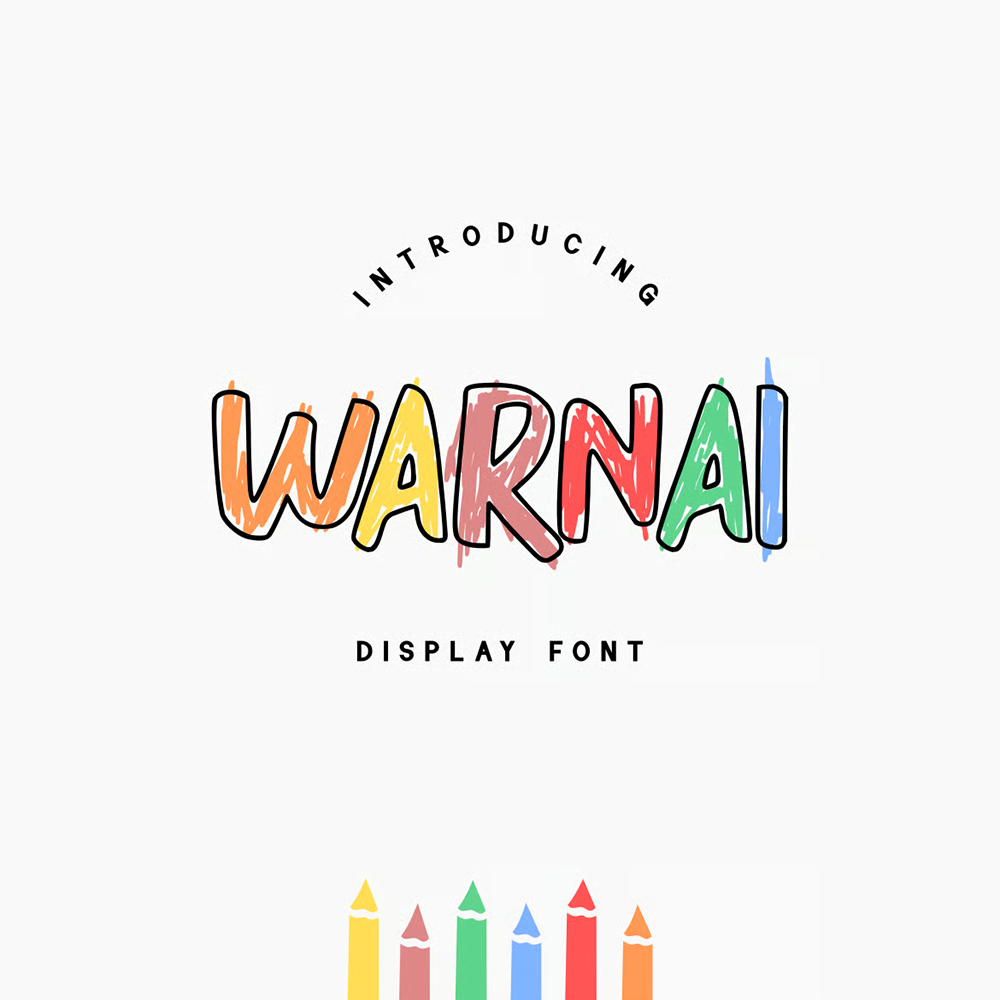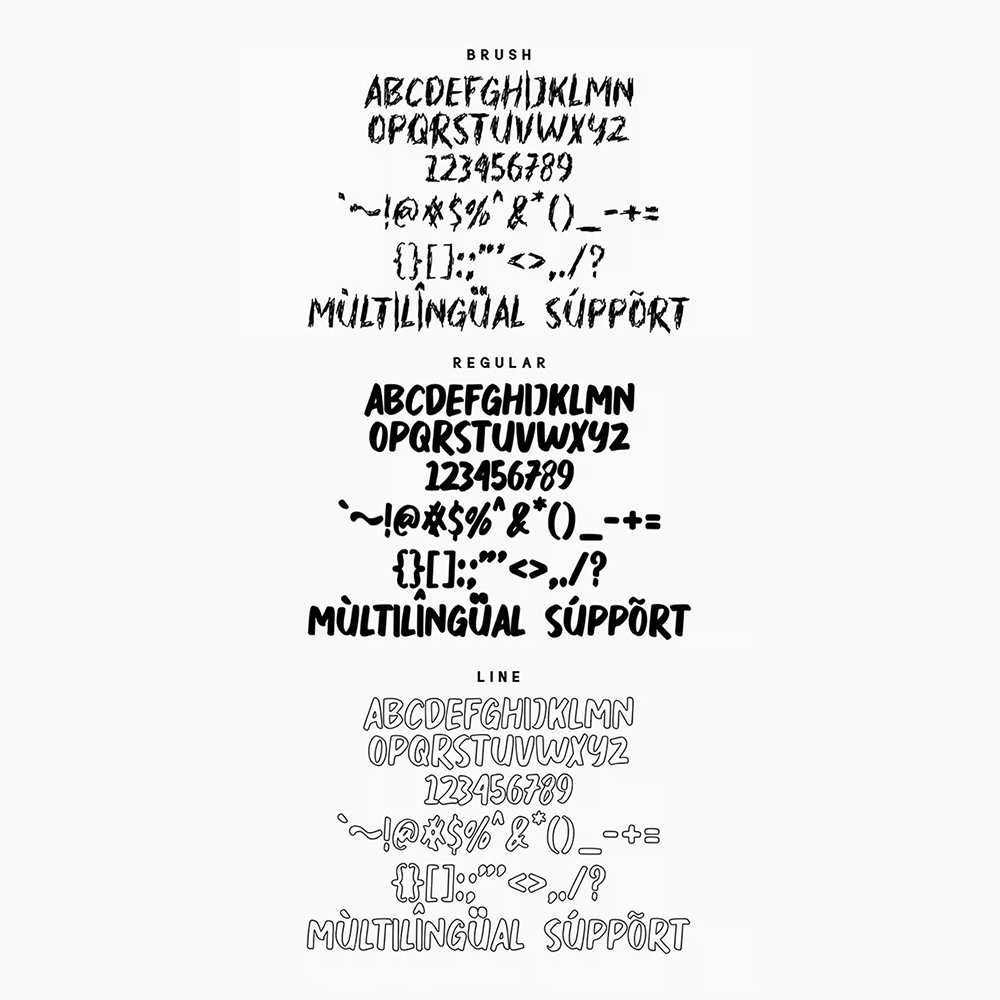
فونت پرمیوم و انگلیسی WARNAI Font یک فونت نمایشی است که سه نوع شکل دارد: نوع اول فونت معمولی، فونت تو خالی و فونت براش (قلممو). فونت بامزه Warnai یک قلم نمایشی انگلیسی مناسب برای استفاده در طرح و پروژههای گرافیکی مختلف به خصوص طرحهای فانتزی کودکانه میباشد. فونت Warnai با سه وزن معمولی، تو خالی و قلمویی طراحی شده است که میتوانید از آن در طراحی پوستر، لباس، تیشرت، بسته بندی محصولات، لوازم التحریر، کتاب، ماگ و لیوان، ظروف یکبار مصرف و… استفاده کنید.